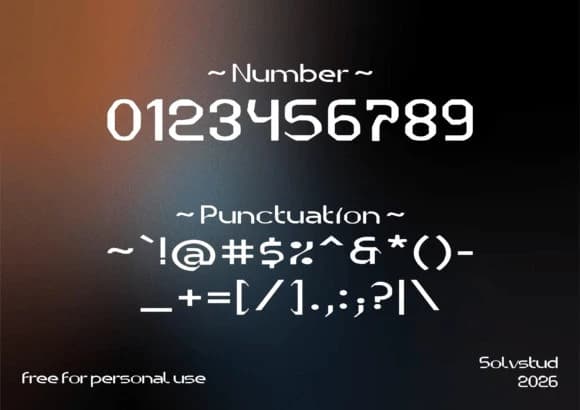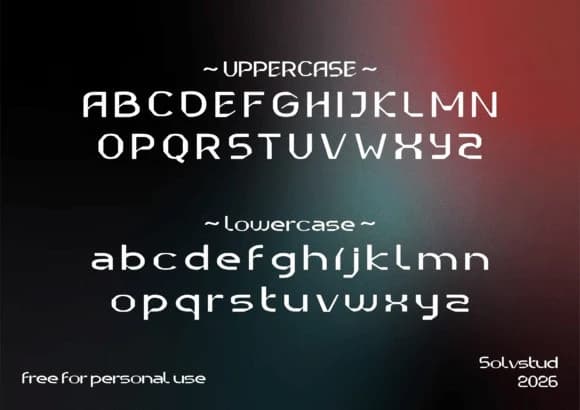
Braven Font
Braven Font, modern ve fütüristik bir yazı tipidir. Bu yazı tipi, temiz geometrik hatlara sahip geniş harf biçimleri ve belirgin, hassas kesimli açıklıklar ile yüksek teknolojik bir sofistikasyon sunar.
Braven Font, modern ve fütüristik bir yazı tipidir. Bu yazı tipi temiz geometrik çizgilere sahip geniş, açık harf biçimlerine ve belirgin, keskin kesimli açıklıklara sahiptir ve yüksek teknolojik sofistikeliği yansıtır.